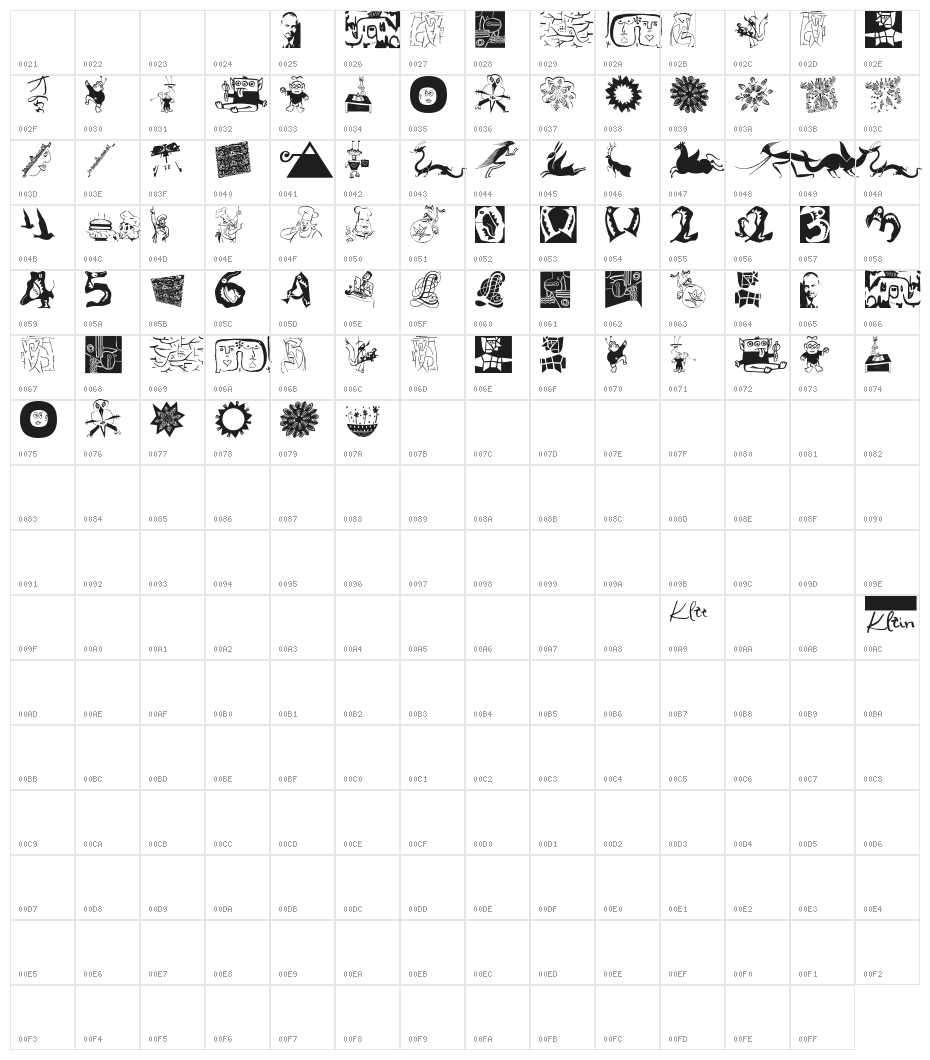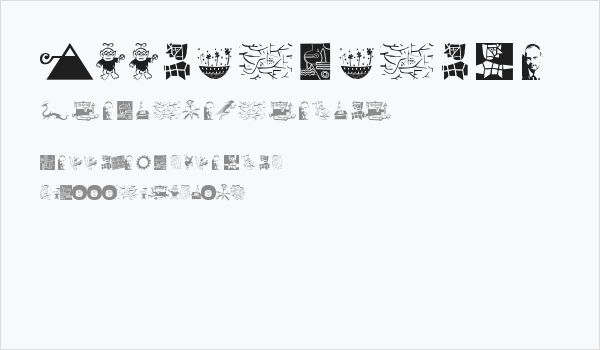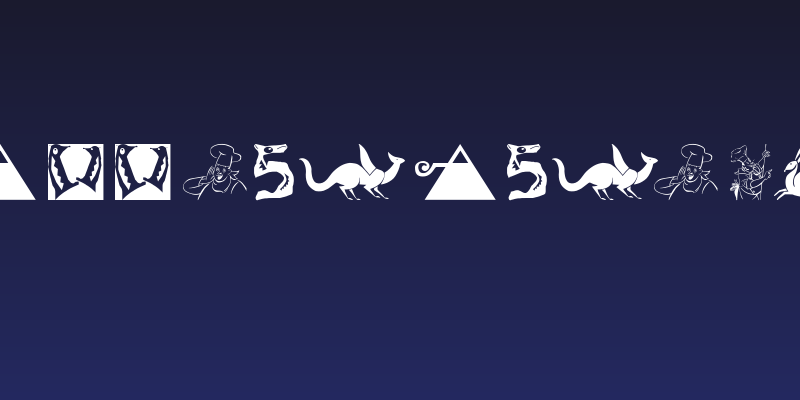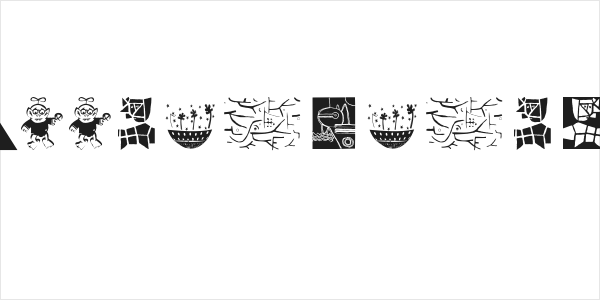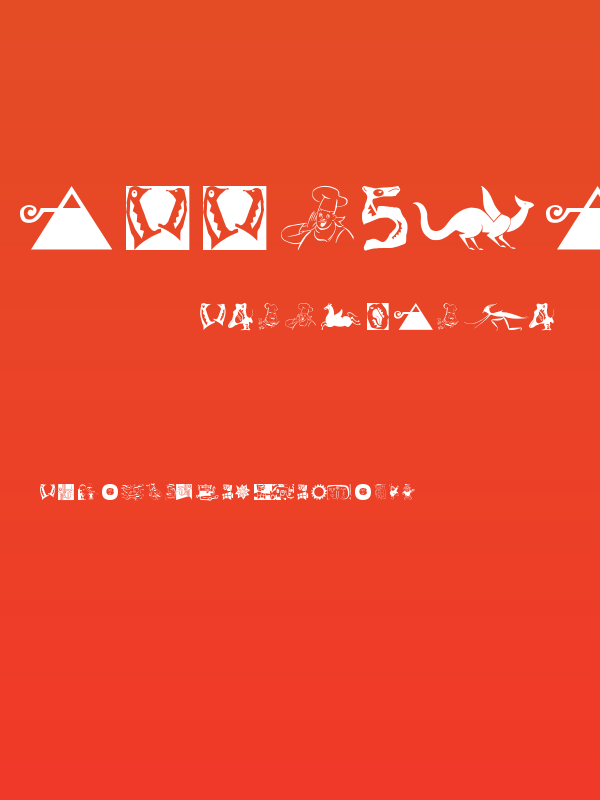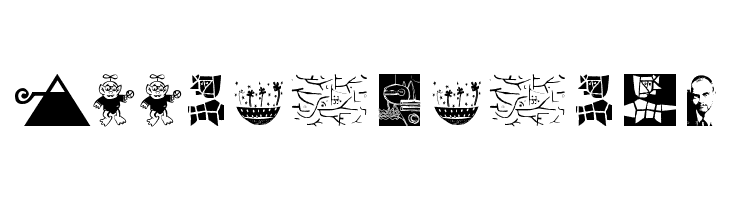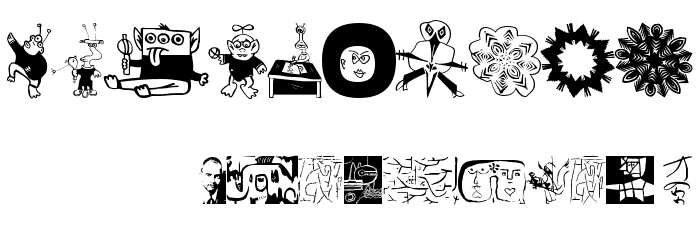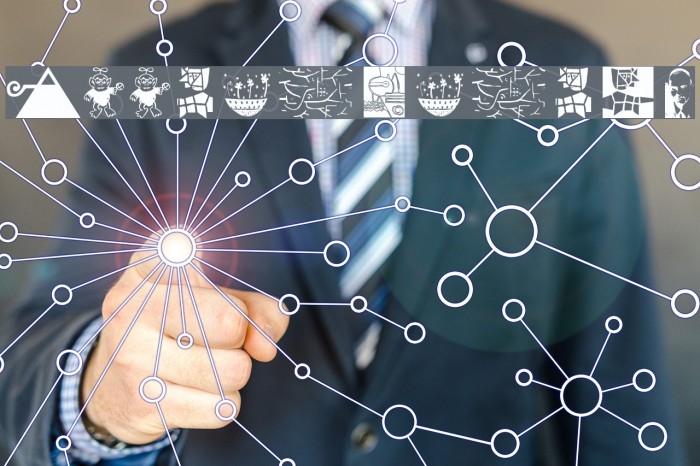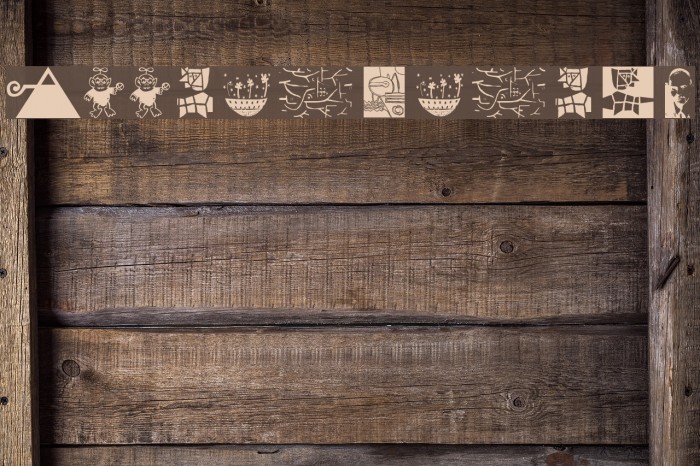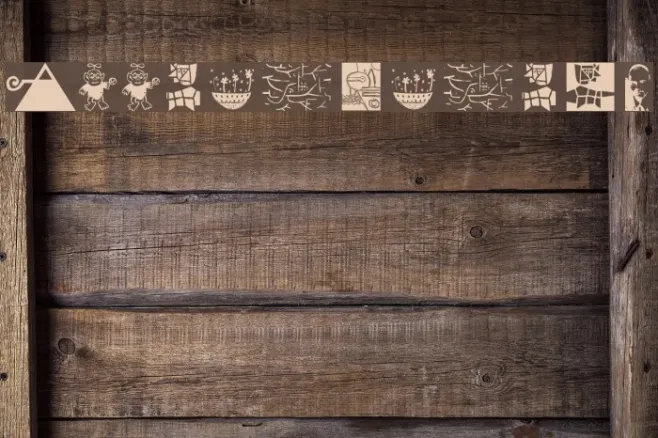
Assoziazione Font
Questo font include 224 caratteri. Clicca su un carattere per vedere i dettagli.
| Caso d'uso | Artistic projects, decorative elements, creative branding. |
| Progetti proposti | Ideal for creative projects such as children's book illustrations, artistic posters, unique branding elements, and decorative design work. |